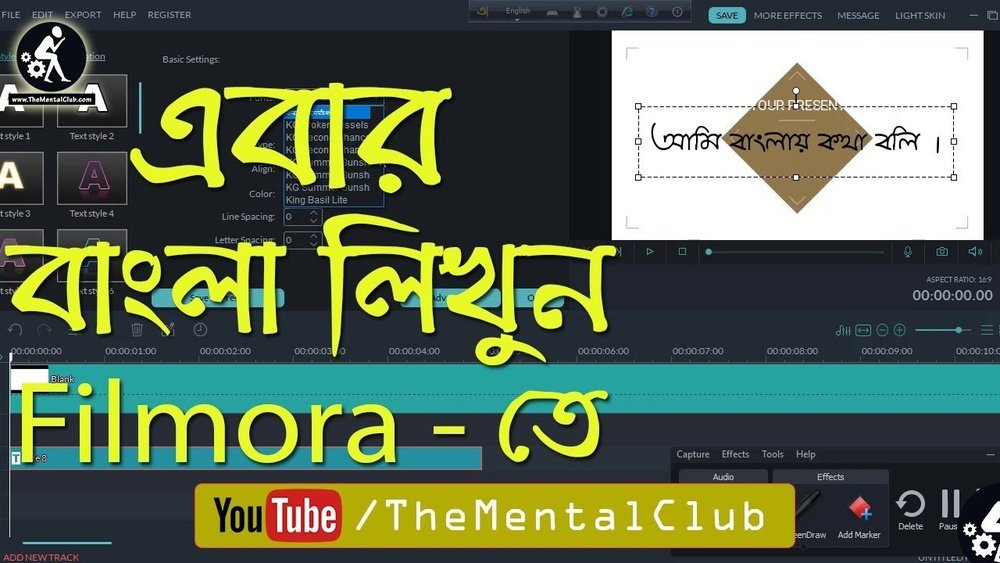
আপনি যদি ফিলমোরা-তে বাংলা ফন্ট ব্যবহার করতে চান, তাহলে আপনি একা নন। অনেক ভিডিও এডিটর চায় ভিডিওতে সুন্দর ও স্পষ্ট বাংলা টেক্সট যোগ করতে, কিন্তু ফিলমোরা-তে বাংলা ফন্ট ইনস্টল করা অনেকের কাছে কঠিন মনে হয়। এই গাইডে, আমি আপনাকে ধাপে ধাপে শেখাবো কিভাবে ফিলমোরা-তে বাংলা ফন্ট ইনস্টল ও ব্যবহার করবেন। আপনি যদি বাংলা ভাষায় ভিডিও তৈরি করেন, তাহলে এই কৌশলগুলো আপনাকে আরও পেশাদার এবং আকর্ষণীয় ভিডিও বানাতে সাহায্য করবে। চলুন, শুরু করা যাক।
বাংলা ফন্ট ব্যবহার সহজ মনে হলেও, ফিলমোরা-র মতো সফটওয়্যারে ঠিকভাবে ফন্ট দেখানোর জন্য কিছু টেকনিক জানা দরকার। অনেক ইউজার প্রথমে চেষ্টা করে ব্যর্থ হয়, কারণ তারা হয়তো ফন্ট ফরম্যাট, কীবোর্ড লেআউট, অথবা সফটওয়্যারের ফন্ট সাপোর্ট সম্পর্কে সঠিক ধারণা রাখেন না। এই গাইডে আপনি ফন্ট ইন্সটল ও ব্যবহার করার প্রতিটি ধাপ, সমস্যা ও সমাধান, ফন্টের পারফরম্যান্স, বিশেষ কৌশল, এবং ভবিষ্যৎ সম্পর্কে বিস্তারিত জানতে পারবেন। একেবারে শুরু থেকে শেষ পর্যন্ত আপনার ভিডিও এডিটিংয়ের বাংলা ফন্ট সংক্রান্ত সব প্রশ্নের উত্তর পাবেন।
ফিলমোরা-তে বাংলা ফন্ট ব্যবহারের প্রয়োজনীয়তা
ভিডিও এডিটিং-এ বাংলা ফন্ট ব্যবহার করার চাহিদা দিন দিন বাড়ছে। বাংলাদেশ ও পশ্চিমবঙ্গের ইউজাররা ভিডিওতে বাংলা ভাষা ব্যবহার করতে চান। ফিলমোরা জনপ্রিয় ভিডিও এডিটিং সফটওয়্যার, কিন্তু ডিফল্টভাবে এতে বাংলা ফন্ট থাকে না। এজন্য আপনাকে আলাদাভাবে ফন্ট ইন্সটল করতে হয়।
অনেক ইউজার ভাবেন ইংরেজি ফন্ট ব্যবহার করলেই হয়, কিন্তু স্থানীয় ভাষায় টেক্সট দিলে ভিডিওর মান এবং দর্শকের আগ্রহ অনেক বেড়ে যায়। বাংলা ফন্ট যোগ করলে ভিডিও শুধু তথ্যপ্রদান নয়, বরং দর্শকের আবেগ, সংস্কৃতি, ও আস্থা অর্জনে সাহায্য করে। বিশেষ করে যখন ভিডিওর লক্ষ্য audience বাংলা ভাষাভাষী, তখন বাংলা ফন্ট না ব্যবহার করলে কনটেন্টের গুরুত্ব কমে যায়।
কেন বাংলা ফন্ট দরকার?
- বক্তব্য স্পষ্ট করা: বাংলা ফন্ট দিয়ে দর্শকদের কাছে বার্তা সহজভাবে পৌঁছানো যায়। ইংরেজি ফন্টে অনেক সময় বাংলা শব্দ ঠিকভাবে লেখা যায় না, ফলে বার্তা বিভ্রান্তিকর হয়। বাংলা ফন্টে লেখা স্পষ্ট ও সুন্দর দেখায়।
- কনটেন্টের বৈচিত্র্য: বাংলা ভাষার কনটেন্ট ইউটিউব, ফেসবুক, টিকটকের মতো প্ল্যাটফর্মে দর্শক বাড়ায়। ইংরেজি বা হিন্দি কনটেন্টের ভিড়ে বাংলা ভিডিও আলাদাভাবে নজরে আসে।
- ব্র্যান্ডিং: স্থানীয় ভাষায় ব্র্যান্ডিং দর্শকের কাছে বিশ্বাসযোগ্যতা বাড়ায়। ব্যবসা, শিক্ষা, সংবাদ, বা বিনোদন—সব ক্ষেত্রেই ব্র্যান্ডের পরিচয় ও আস্থা গড়ে তুলতে বাংলা ফন্ট বিশেষ ভূমিকা রাখে।
একটি জরিপে দেখা গেছে, বাংলাদেশে ৭৫% ভিডিও কনটেন্ট ক্রিয়েটর স্থানীয় ভাষা ব্যবহার করেন। এই তথ্য শুধু সংখ্যা নয়—এটি বলে দেয়, যারা বাংলা ফন্ট ব্যবহার করে, তারা audience-এর সঙ্গে সহজেই সংযোগ তৈরি করতে পারেন। ইউটিউব, ফেসবুক, এবং টিকটকের মতো প্ল্যাটফর্মে বাংলা ভাষায় ভিডিও বানালে engagement বাড়ে, comment ও share সংখ্যা বেশি হয়। অনেক বড় ব্র্যান্ডও এখন স্থানীয় ভাষায় কনটেন্ট বানাচ্ছে, কারণ এতে দর্শক loyalty বাড়ে।
অনেকে হয়তো ভাবে, শুধু subtitle দিলেই হয়। কিন্তু subtitle-এর চেয়ে টাইটেল, description, বা ইন-ভিডিও টেক্সট audience-কে বেশি আকৃষ্ট করে। বাংলা ফন্ট দিয়ে আপনি storytelling, product explanation, অথবা tutorial আরও সহজভাবে উপস্থাপন করতে পারবেন।
ফিলমোরা কোন ফন্ট ফরম্যাট সাপোর্ট করে?
ফিলমোরা TrueType (.ttf) এবং OpenType (.otf) ফন্ট ফরম্যাট সাপোর্ট করে। বাংলা ফন্টের বেশিরভাগই .ttf ফরম্যাটে পাওয়া যায়।
অনেক ইউজার PostScript বা পুরনো ফন্ট ব্যবহার করেন, যা ফিলমোরা-তে কাজ করে না। ফরম্যাট ঠিক না হলে ফন্ট ইনস্টল হলেও ফিলমোরা-তে দেখা যায় না বা অক্ষর কেটে যায়।
| ফন্ট ফরম্যাট | সাপোর্টেড? | বাংলা ফন্টের প্রাপ্যতা |
|---|---|---|
| TrueType (.ttf) | হ্যাঁ | বেশি পাওয়া যায় |
| OpenType (.otf) | হ্যাঁ | কিছু পাওয়া যায় |
| PostScript | না | দুষ্প্রাপ্য |
অভিজ্ঞরা বলেন, ইউনিকোড সাপোর্টড. ttf ফন্ট ফিলমোরা-তে সবচেয়ে ভালো কাজ করে। কিছু ফন্ট আছে যেগুলো শুধু Windows বা শুধু Mac-এ ঠিকভাবে দেখায়, তাই ডাউনলোড করার সময় ফন্টের compatibility দেখে নিন।
জনপ্রিয় বাংলা ফন্ট
ফিলমোরা-তে ব্যবহারযোগ্য কিছু বাংলা ফন্ট:
- SolaimanLipi: বাংলাদেশে সবচেয়ে জনপ্রিয়। ক্লিন লুক, স্পষ্ট অক্ষর।
- Siyam Rupali: Government ও educational কাজে ব্যবহৃত হয়।
- Nikosh: সংবাদ ও সরকারি নথিতে প্রচলিত।
- Kalpurush: আধুনিক ও সহজ পড়ার জন্য ভালো।
- Bangla: Basic ও traditional look।
- AdorshoLipi: Creative design ও পোস্টার বানাতে ভালো।
এই ফন্টগুলো সহজেই ডাউনলোড করা যায় এবং ফিলমোরা-তে ব্যবহার করা যায়। SolaimanLipi ও Siyam Rupali সবচেয়ে বেশি ব্যবহার হয়, কারণ এদের ফরম্যাট সহজ, অক্ষর স্পষ্ট, এবং ইউনিকোড সাপোর্ট করে। অনেকে creative purposes-এ AdorshoLipi বা Kalpurush বেছে নেন।
কিছু ফন্ট রয়েছে যেগুলো বিশেষ purposes-এ ব্যবহার হয়, যেমন শিক্ষামূলক ভিডিওতে Nikosh, বা ফ্যাশন ভিডিওতে Kalpurush। ফন্ট বাছাই করার সময় audience ও content type মাথায় রাখুন।
Mac-এ বাংলা ফন্ট ইন্সটল করলে ফিলমোরা-তে সমস্যা হয়?
Mac-এ Font Book দিয়ে বাংলা ফন্ট ইন্সটল করলে সাধারণত কোনো সমস্যা হয় না। তবে ফন্ট ফাইলের ফরম্যাট (. ttf) ঠিক আছে কিনা চেক করুন।
বাংলা ফন্ট ফিলমোরা-তে ব্যবহার করা এখন আর কঠিন নয়। আপনি এই গাইড মেনে চললে সহজেই ভিডিওতে বাংলা ভাষা ব্যবহার করতে পারবেন। ভিডিও এডিটিংয়ে বাংলা ফন্ট যোগ করলে কনটেন্ট আরও আকর্ষণীয় ও পেশাদার হবে। আজই চেষ্টা করুন এবং আপনার ভিডিওতে নতুন মাত্রা যোগ করুন।